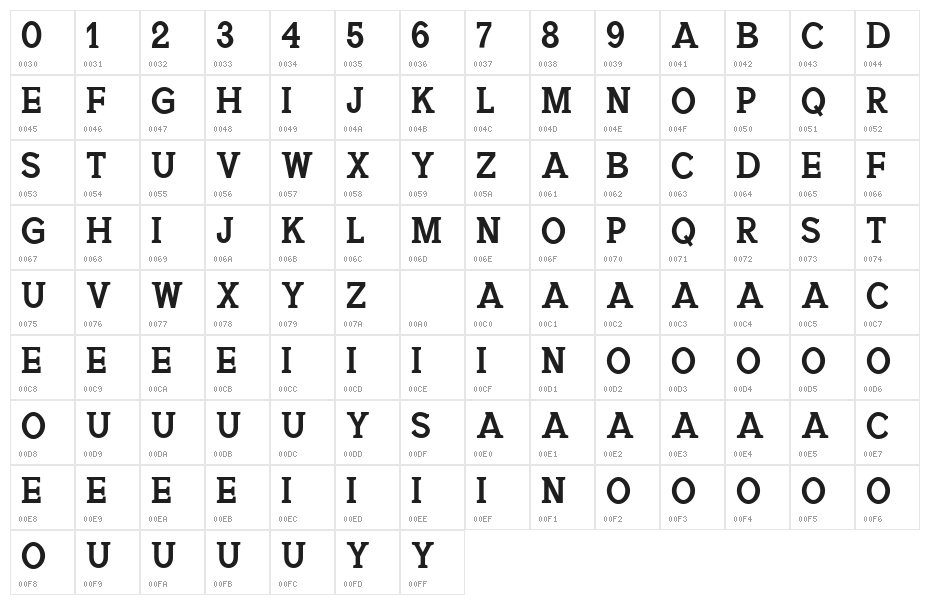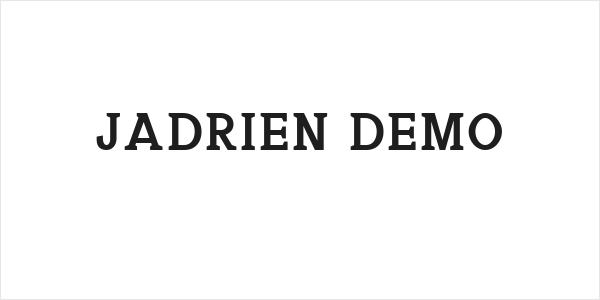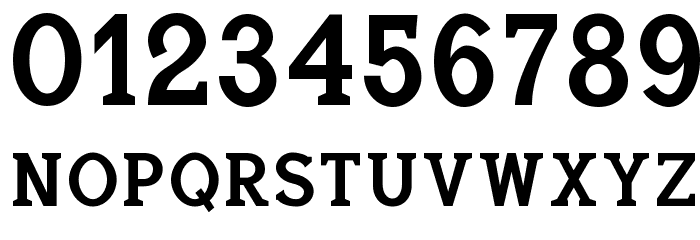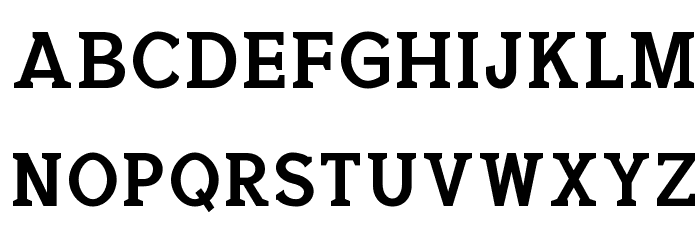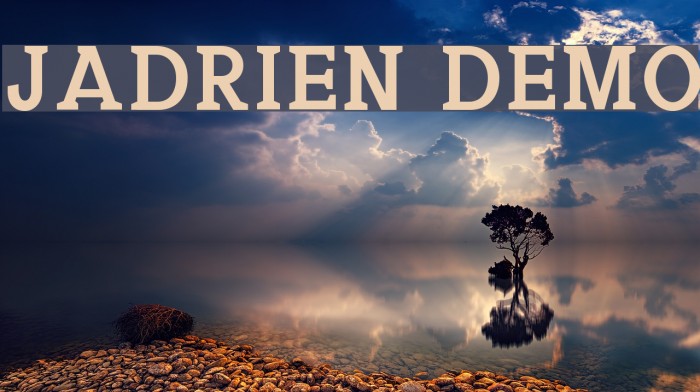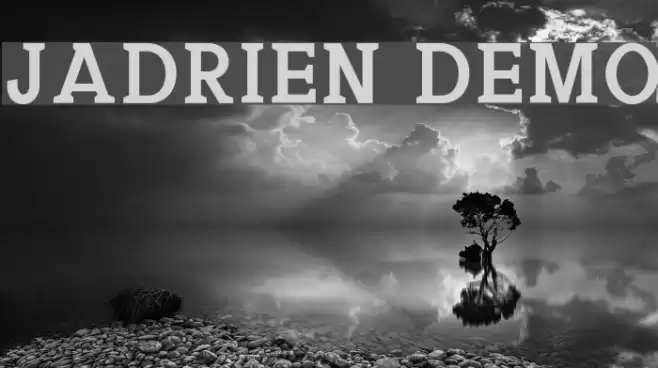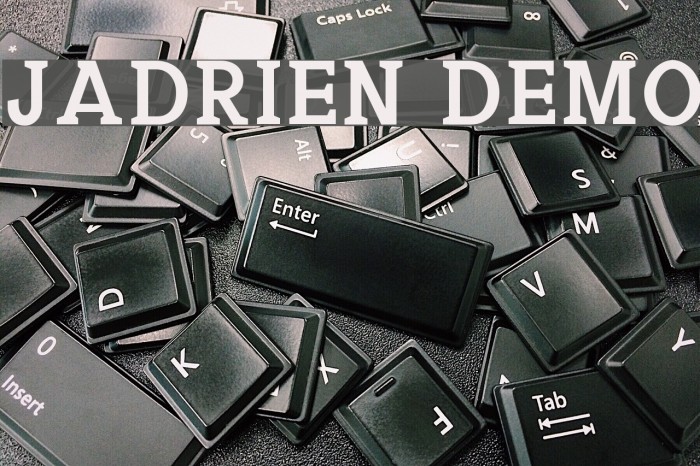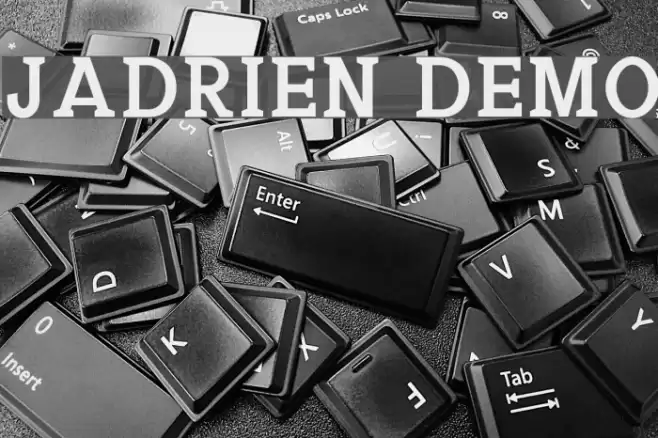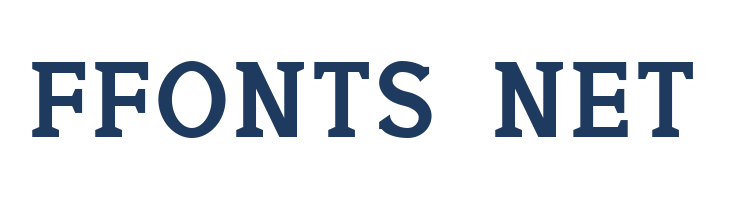
Jadrien Demo Font
✎ Serif
| Catégories | Serif |
| Style général | Classic |
| Projets proposés | Ideal for book covers, formal invitations, editorial design, and branding projects that require a traditional and authoritative look. |